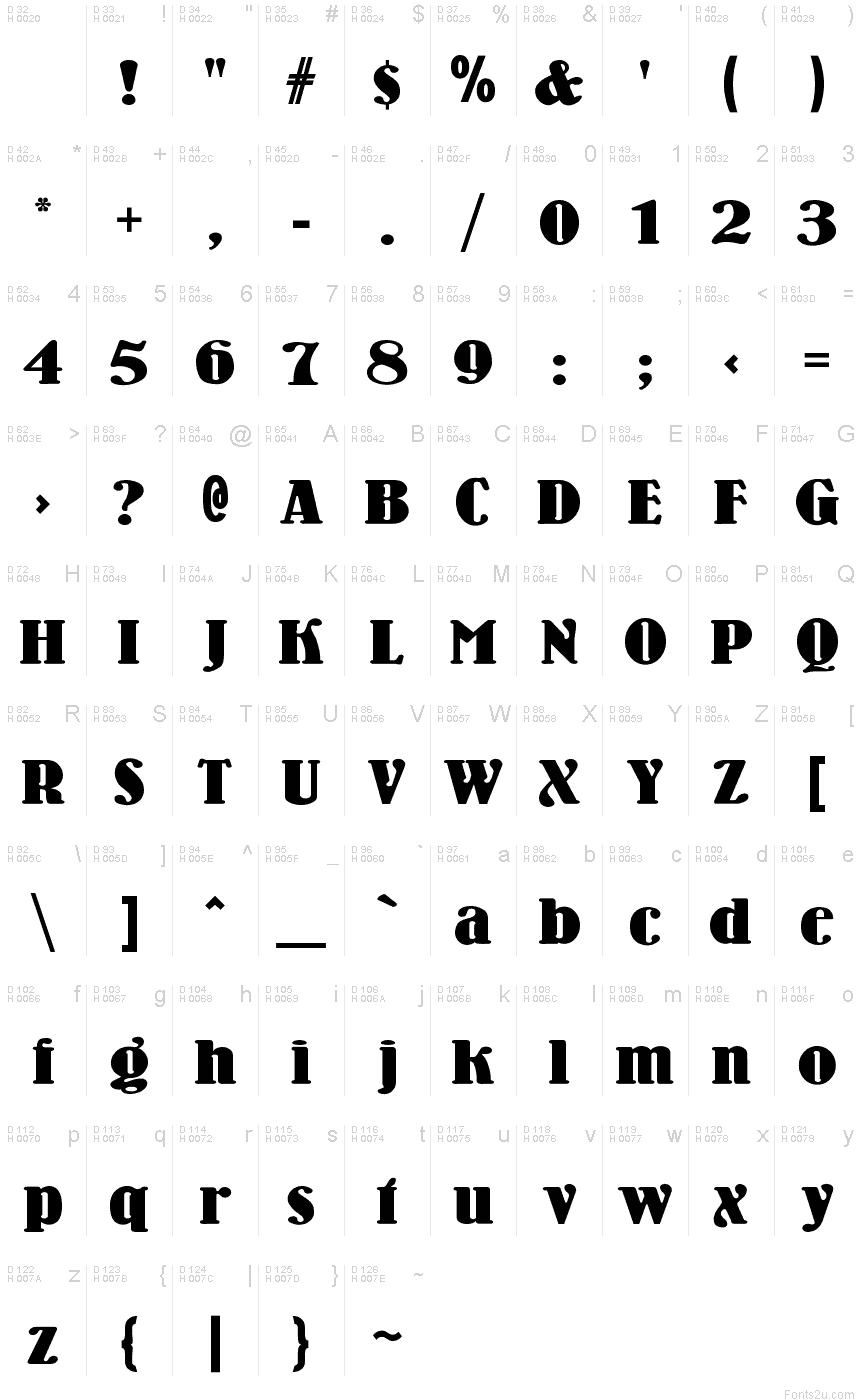
Wooden Nickel Black autorstwa Nicka Curtisa to darmowy, retro krój typu display, stylizowany na tradycyjne czcionki drewniane. Ciężkie, przypominające monety litery oraz głębokie wcięcia sprawiają, że znaki wyglądają jak odbite pieczątką, a nie tylko narysowane. Litery opierają się na szerokich szeryfach, obłych kształtach i delikatnej nostalgii, która przenosi prosto w klimat plakatów z przełomu wieków.
Ten styl świetnie sprawdzi się na opakowaniach, w brandingu barów i restauracji, nagłówkach plakatów, okładkach albumów czy tytułach, gdzie ten darmowy krój musi szybko nadać całości solidny, vintage charakter. Sprawdza się również w przypadku monogramów i krótkich napisów, ponieważ gęste sylwetki i żłobione wnętrza sprawiają, że nawet kilka liter ma wyrazistą, konkretną formę.